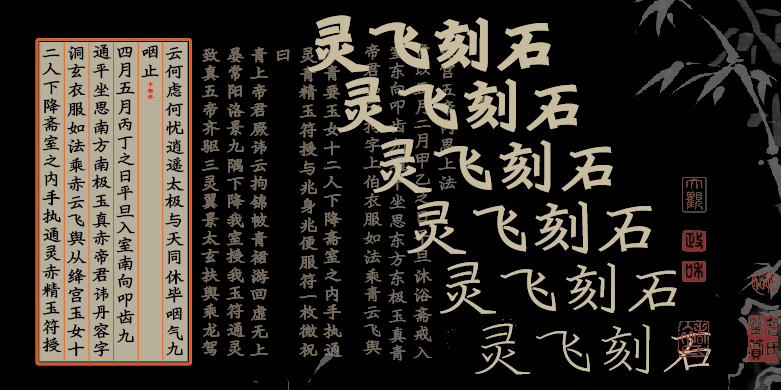
方正灵飞刻石家族
字体品牌: 方正字库 设计师:王贝宁 字体分类:创意字体、楷体、混合、黑体 字体属性:精品字 字符集:大陆简体(GB2312-80) 发布时间: 2024
灵飞刻石是一款结构借鉴钟绍京小楷灵飞经,笔型采取了黑体化处理的一款融合字体,最终效果有碑刻金石之风,也因此命名为 “灵飞刻石”,设计理念为用字体设计的眼光重新归纳楷体,统一笔画和气质,分类上可以划入黑楷这个类别,是书法字体黑体化的一个尝试,日本字体设计师 味冈伸太郎 也曾做过同样的设计尝试,方正字库也已有方正黑楷,方正古仿这样的产品。
本款字体包含6个字重,细体到中粗体都可用于小字排版,颇有钢笔手写意味,横排会有一些跃动的活泼感;粗体则更像碑刻,可以用于诸如:文化类展览标题和品牌招牌等大字场景,也欢迎广大设计师可以应用到更多合适的地方!